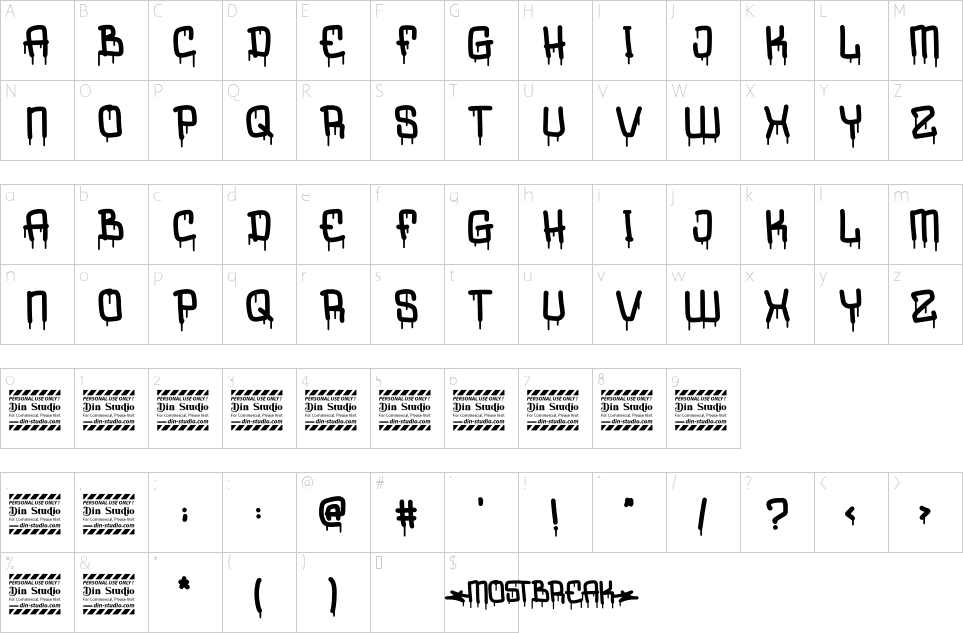
A fonte ‘Mostbreak Font’ é uma opção fresca e moderna para quem busca um estilo diferente para seus projetos digitais. Desenhada pelo Din Studio, essa fonte oferece um ar de contemporaneidade que pode se adequar a uma variedade de aplicações, desde textos simples até materiais mais elaborados. Com um design único e versátil, ‘Mostbreak Font’ está disponível tanto para sistemas Windows quanto para Mac, permitindo que você adicione esse toque especial aos seus documentos, banners ou qualquer outro projeto digital. Com a possibilidade de baixar e usar essa fonte gratuitamente, é uma ótima maneira de explorar um novo e atraente estilismo para suas criações digitais. E embora não tenha um designer específico atribuído, a fonte já foi baixada por 853 usuários, o que é uma indicação de sua popularidade e desempenho. Se você está procurando por uma fonte que não pareça tão comum, ‘Mostbreak Font’ pode ser o caminho para você.